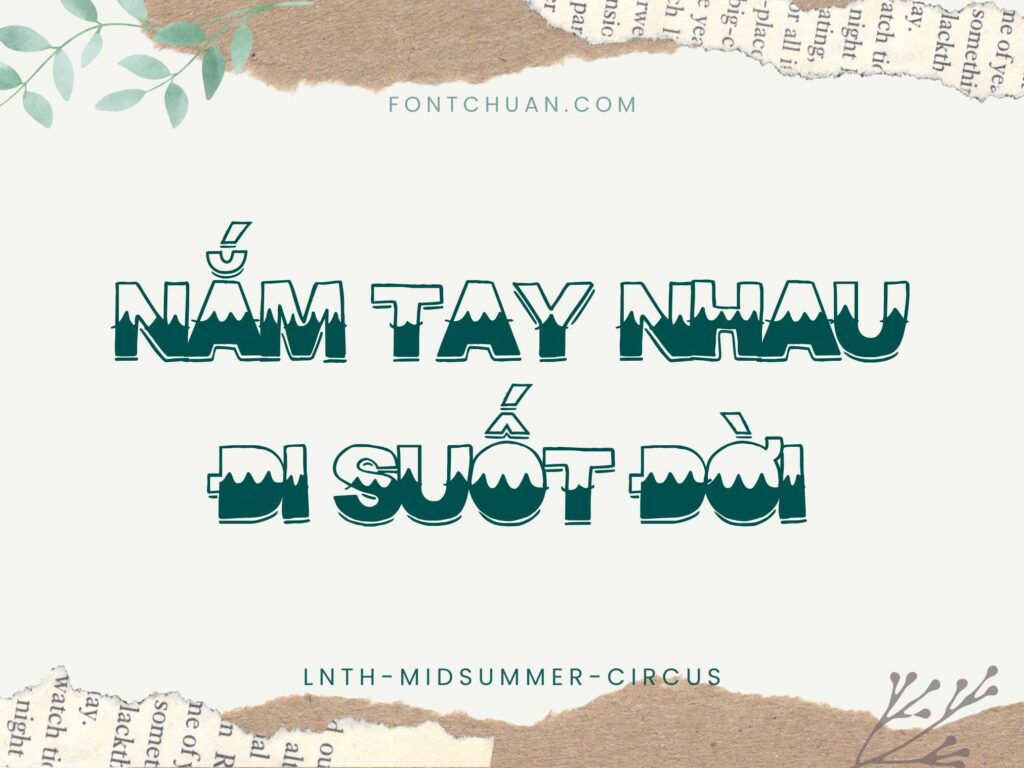
Font LNTH Midsummer Circus Việt Hóa
Font Midsummer Circus là một font chữ mang phong cách vui nhộn, mang đậm tinh thần của những gánh xiếc và lễ hội mùa hè. Với thiết kế đầy màu sắc, các ký tự có sự phá cách nhẹ nhàng, font này mang lại cảm giác phấn khích, tươi vui và đầy năng lượng. Midsummer Circus rất phù hợp để sử dụng trong các thiết kế poster, banner, quảng cáo hoặc các nội dung dành cho trẻ em
Phiên bản này đã được Việt hóa bởi LNTH, hỗ trợ đầy đủ tiếng Việt cùng hơn 50 ngôn ngữ khác, giúp người dùng dễ dàng ứng dụng trong thiết kế quốc tế. Font Midsummer Circus được các thành viên Font Chuẩn sưu tầm và đăng tải nhằm cung cấp một lựa chọn sáng tạo, phù hợp cho các dự án mang phong cách lễ hội, vui nhộn
Về đặc điểm thiết kế, Midsummer Circus có các đường nét uốn lượn sinh động, với kiểu chữ mang tính trang trí cao, tạo nên điểm nhấn độc đáo cho các thiết kế. Kiểu chữ này rất phù hợp để sử dụng trong typography sáng tạo, thiết kế thiệp mời, tiêu đề sự kiện, hoặc in ấn quảng cáo
Font Midsummer Circus được ứng dụng rộng rãi trong các sự kiện như lễ hội, sinh nhật, hoặc các thiết kế mang phong cách sôi động. Nó phù hợp với nhiều ngành nghề như quảng cáo, giáo dục, bất động sản, công nghệ